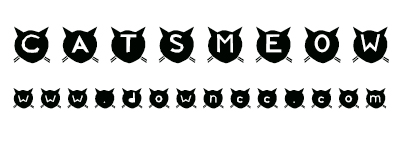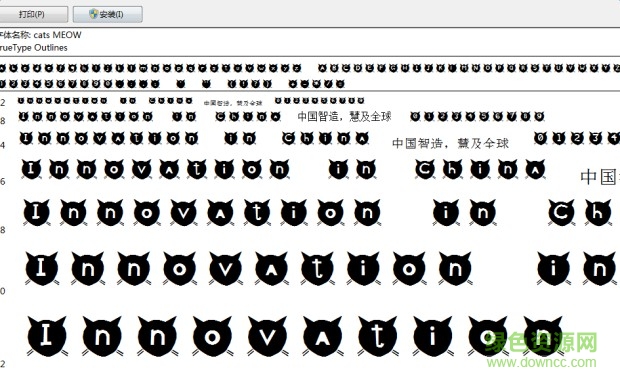
catsmeow字體風(fēng)格真的是太好看了。有點(diǎn)像貓咪字體,每一個(gè)英文字母都被一個(gè)貓貓頭包裹著,非??ㄍó?huà)??梢杂脕?lái)設(shè)計(jì)兒童類作品!歡迎下載使用。
Catsmeow字體是英文字體庫(kù)中的一款個(gè)性字體,可應(yīng)用于廣告計(jì)、藝術(shù)創(chuàng)作、平面設(shè)計(jì)、印刷包裝等領(lǐng)域,喜歡的朋友可免費(fèi)下載收藏。